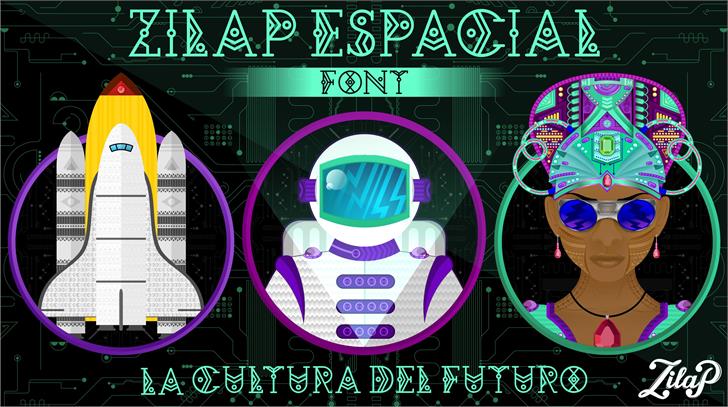
Zilap Espacial Font
Zilap Espacial Font — By ZILAP ZP
Esta fuente esta basada en un enfoque espacial y futurista, perfecta para manejar conceptualizar proyectos sobre el espacio exterior, proyectos con enfoques Futuristas, alienigenas o galacticos.
Zilap Estudio “La Cultura del Futuro”